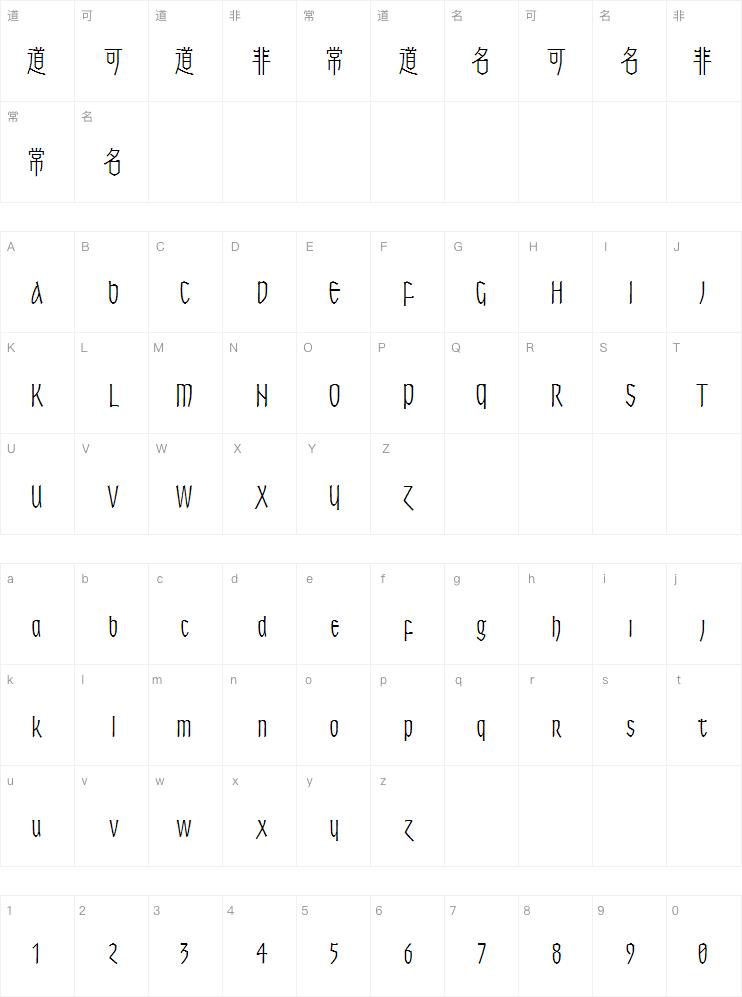
汉仪昆仑篆家族,以昆仑山脉为灵感,字形窄长挺拔如雪山耸立,轮廓简洁锐利;在汉字骨架中融入山石的硬朗,金石刀刻营造出字体的史诗质感。 家族共包含7种字重,细款颇具铁线篆书的细劲刚硬,粗款形似青铜兵器的雄浑厚重,满足不同视觉层级的排版需求,独具历史感与神秘感,适用于传统神话故事、民族品牌标识、双语出版物、历史文化艺术、文博文旅等使用场景。